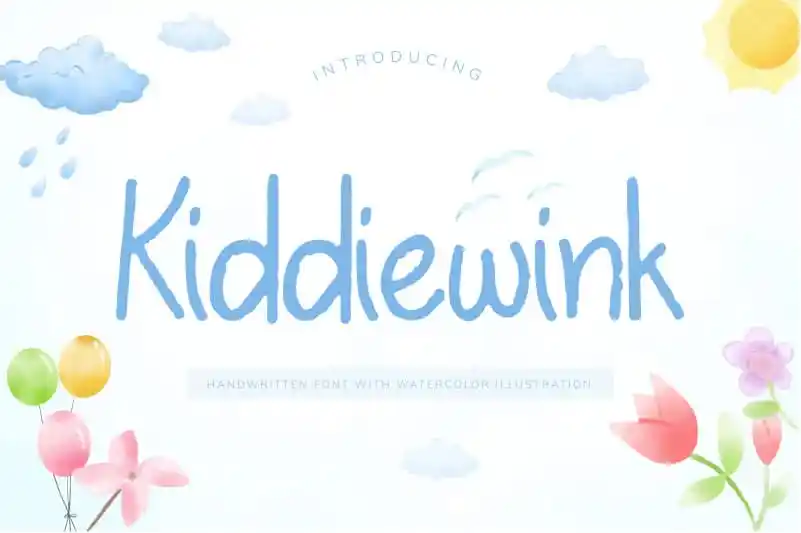
Kiddiewink Handwritten Font – Download Grátis
A Kiddiewink Handwritten Font é uma escolha perfeita para designers buscando dar um toque especial aos seus trabalhos comuns. Suas letras são suaves e amigáveis, criando uma sensação de naturalidade única. Esta fonte se destaca por sua personalidade, oferecendo designs únicos para um amplo range de aplicativos. Seja em cartazes, websites ou editoriais, ela é ideal para manter sua identidade visual vibrante e atraente. Ela se encaixa perfeitamente como uma peça-chave na coleção dos recursos gráficos que designers buscam para dar vida aos seus projetos.